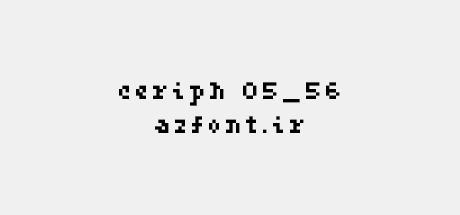
فونت زیبای رایگان ceriph 05_56
قلم زیبای ceriph 05_56 از سری قلم های بسیار زیبا برای تایپوگرافی و لوگو تایپ می باشد.این قلم در وزن Regular و توسط Regenerated by Nadim Shaikli طراحی و منتشر شده است.